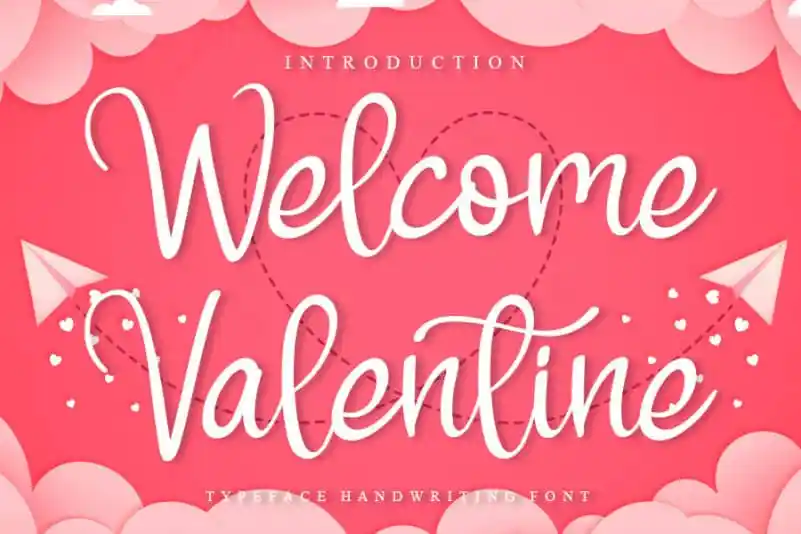
A Welcome Valentine Font é uma criação singular do designer creativeletter, oferecendo aos amantes do design uma experiência memorável com linhas delicadas e letras redondas. Esta fonte escrita à mão é perfeita para criar mensagens de amor e felicidade em qualquer projeto gráfico, seja em cartões de aniversário, selos personalizados ou até mesmo em posters românticos. Com seus traços leves e cores suaves, a Welcome Valentine Font cria um ambiente encantado e acolhedor que torna seu trabalho ainda mais especial. Sempre que você adicionar essa fonte aos seus projetos, o resultado final será uma explosão de charme e romantismo, fazendo das suas criações verdadeiras obras de arte.